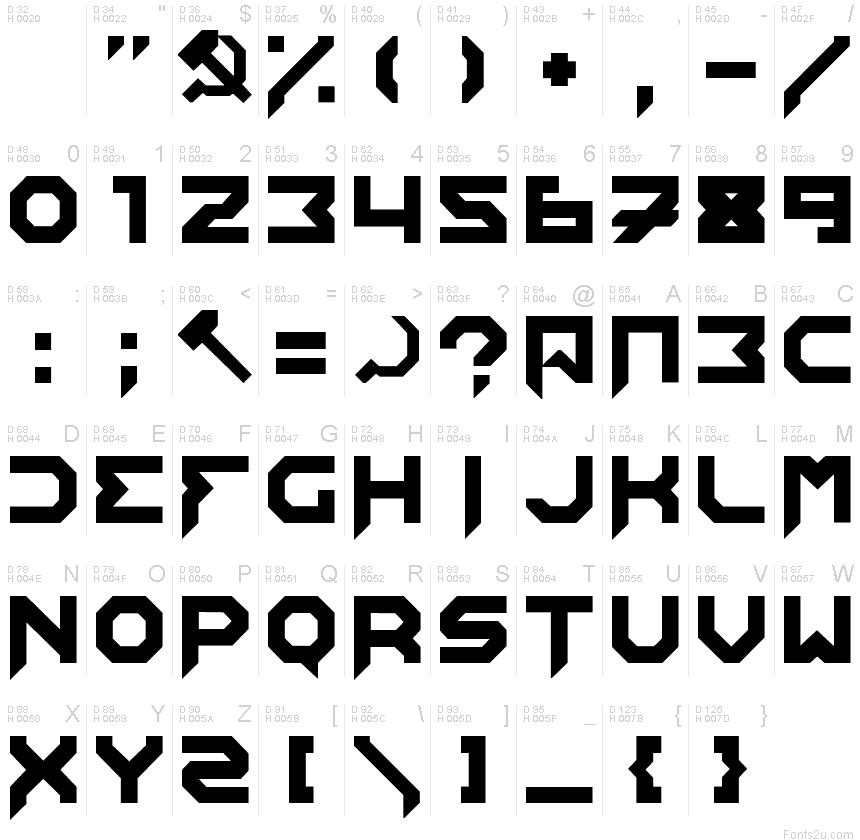
Edistys von 2 the Left Typefaces ist eine kostenlose, futuristische Techno-Display-Schriftart, die aussieht, als wäre sie aus gefaltetem Metall geschnitten. Ihre scharfen Winkel, abgeschrägten Kanten und kompakt angeordneten Formen erzeugen einen markanten, mechanischen Rhythmus, der sofort Sci-Fi- und Cyber-Stimmung vermittelt. Die Buchstaben wirken eher konstruiert als gezeichnet, was Titeln und Logos eine starke technische Identität verleiht, ohne dabei an Lesbarkeit zu verlieren.
Mit Edistys erhältst du eine markante, industrielle Stimme, die bei Gaming-Logos, E-Sport-Branding, Sci-Fi-Filmtiteln, Event-Postern, Album-Covern und Tech-Produktverpackungen glänzt. Diese kostenlose Schrift liebt große Formate, in denen ihre facettierte Geometrie voll zur Geltung kommt. Für eine klare Hierarchie kombiniere Edistys mit einer sauberen, neutralen serifenlosen Schrift für den Fließtext und nutze Edistys gezielt für Schlagzeilen und Wortmarken, um ein prägnantes und lesbares Layout zu gewährleisten.
Edistys